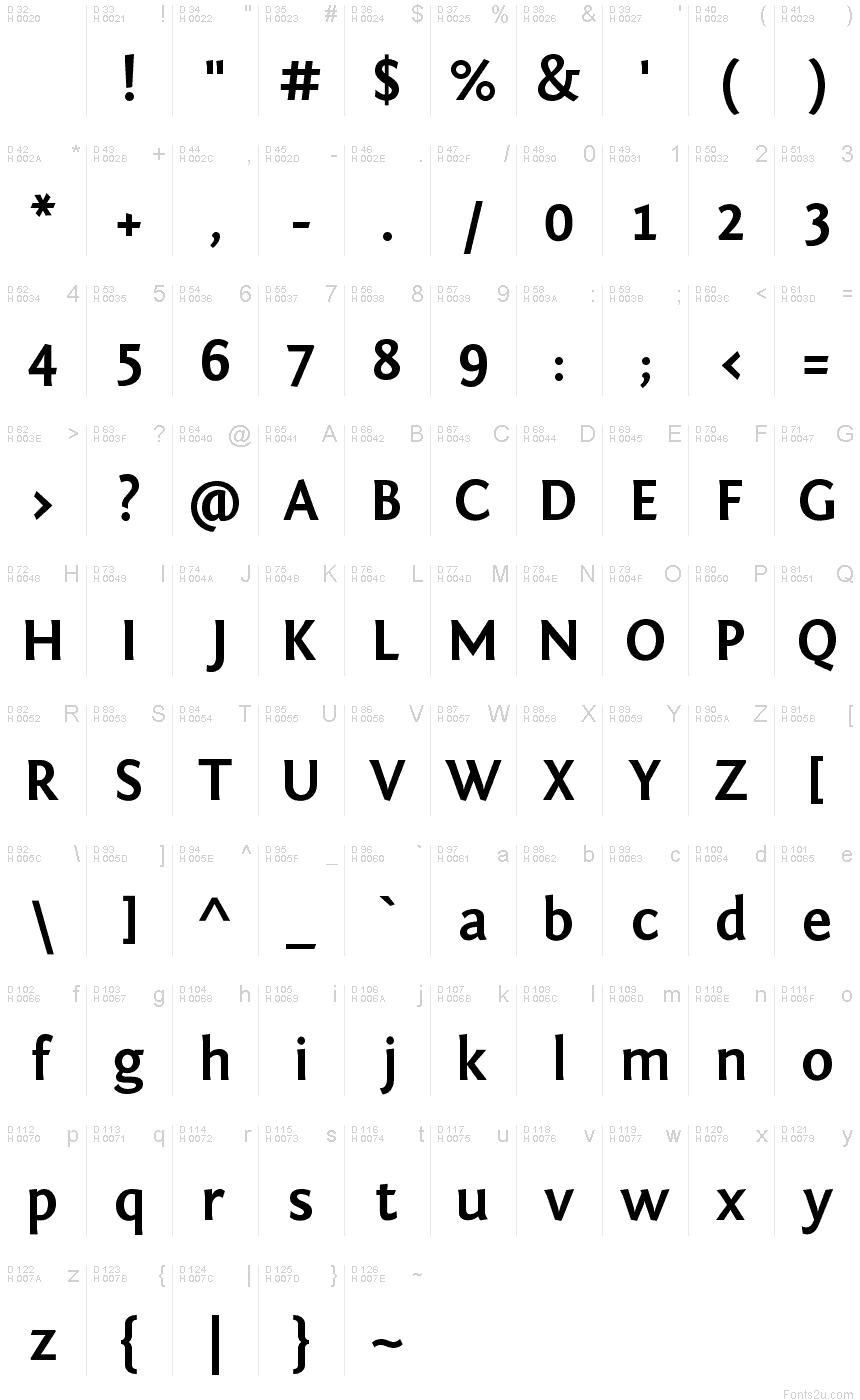
FontinSansCR-Bold
Fontin Sans CR Bold od Josa Buivengy je bezplatné humanistické bezpatkové písmo s pevnými tahy a jemně kaligrafickými tvary. Široké křivky a měkce se zužující napojení brání tomu, aby písmena působila striktně geometricky.
Vedle redakční ilustrace mohou silné tvary sloužit jako klidný typografický protipól k volným kresbám nebo strukturované fotografii. Hodí se na obálky časopisů, kulturní plakáty a knižní přebaly, kde značná tloušťka podpoří přehledné a sebevědomé titulky. Spojení robustní konstrukce a lidského detailu se hodí zejména pro nakladatelské a umělecké projekty zaměřené na řemeslo, literaturu nebo současnou kulturu.